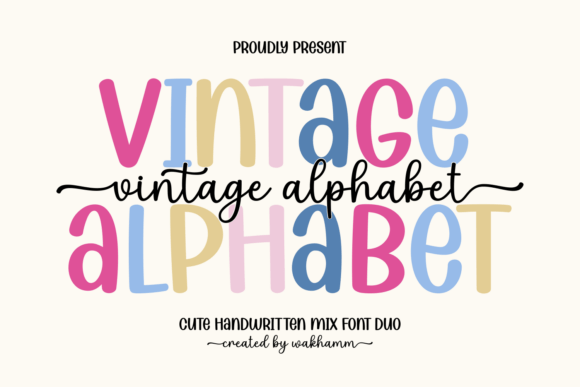
Vintage Alphabet
Die richtigen Designelemente zu finden, kann eine Herausforderung sein, aber Vintage Alphabet bietet eine außergewöhnliche Sammlung, die Ihre Arbeit sofort aufwertet.
Egal, ob Sie POD-Produkte (Print on Demand), Hochzeitseinladungen oder Social-Media-Grafiken erstellen, Vintage Alphabet ist die ideale Wahl.